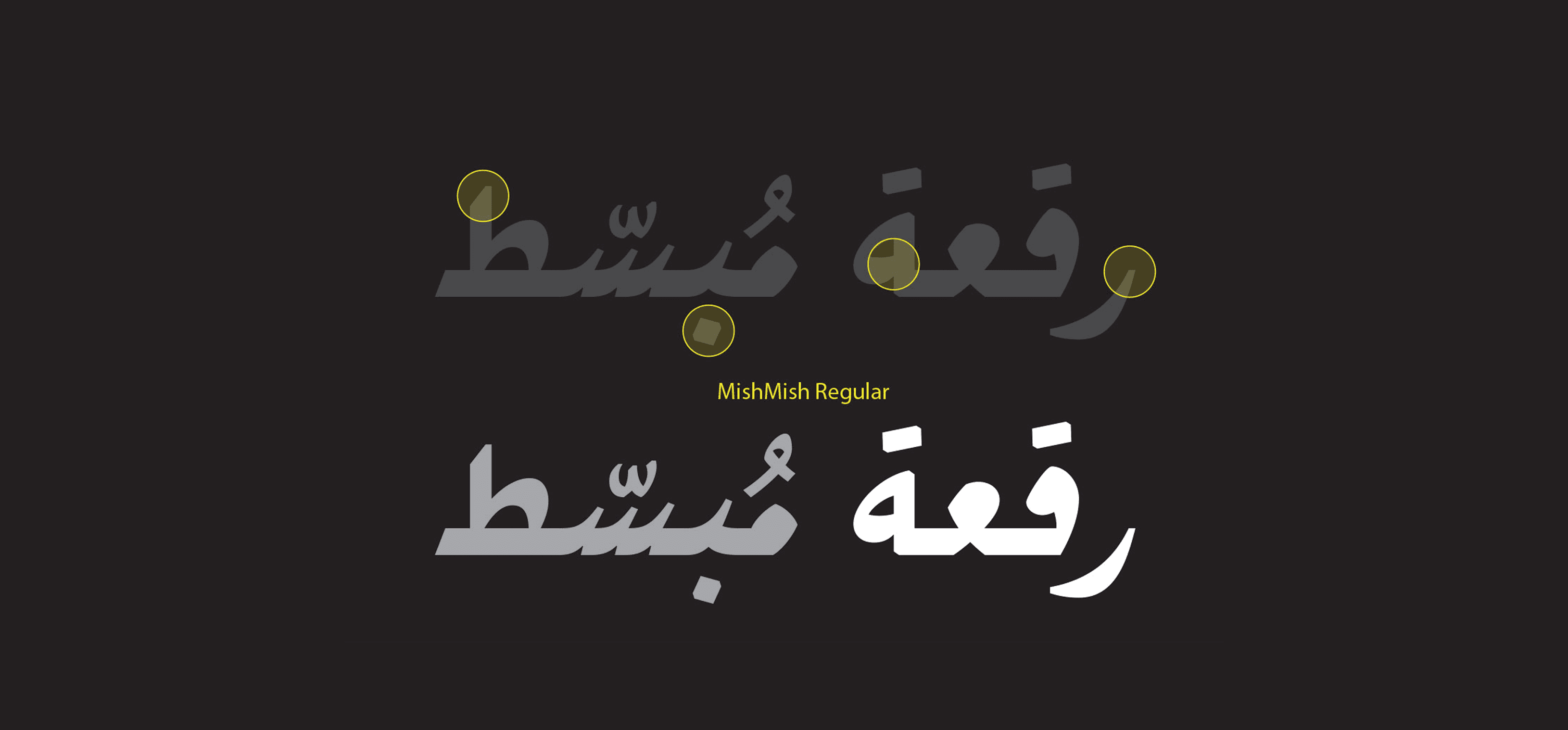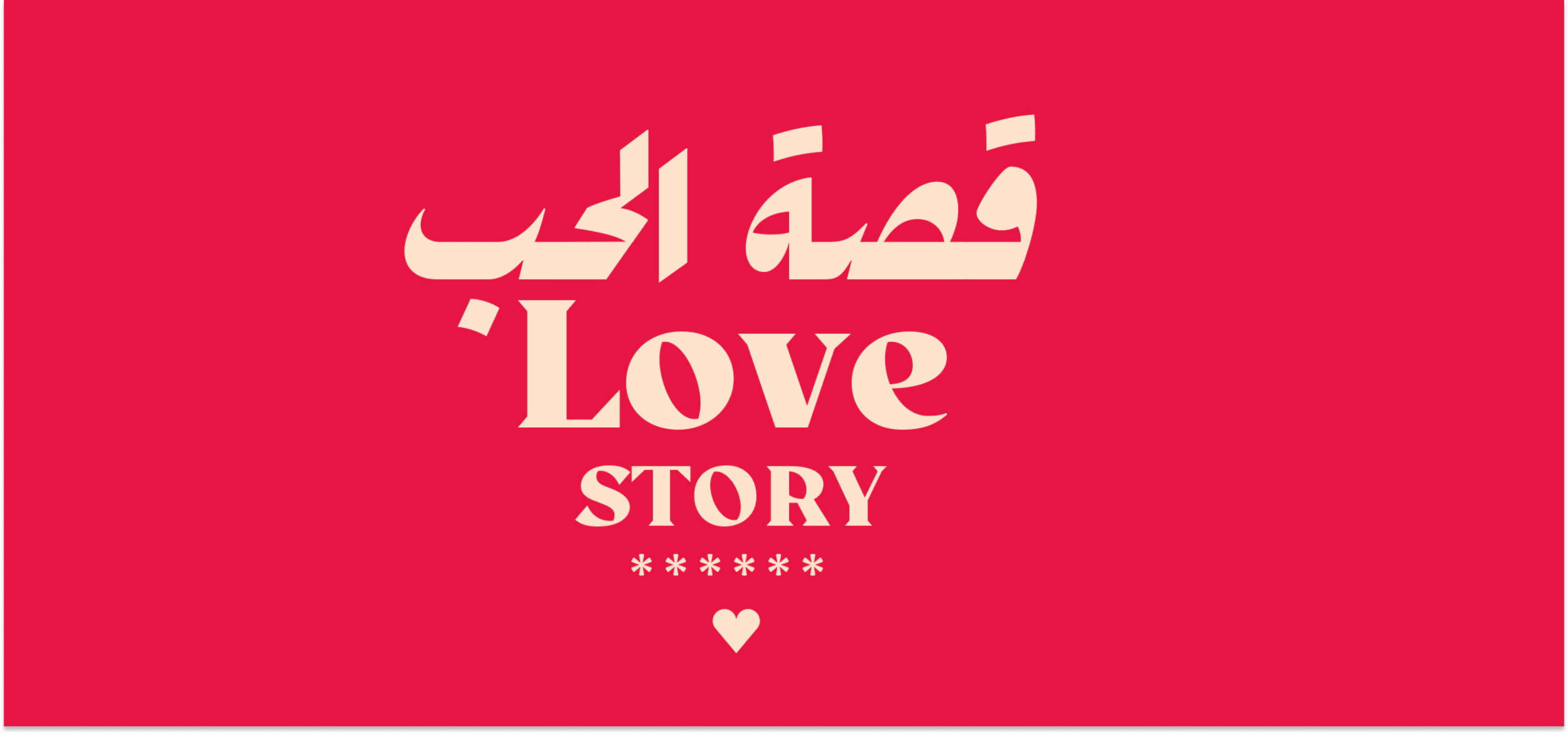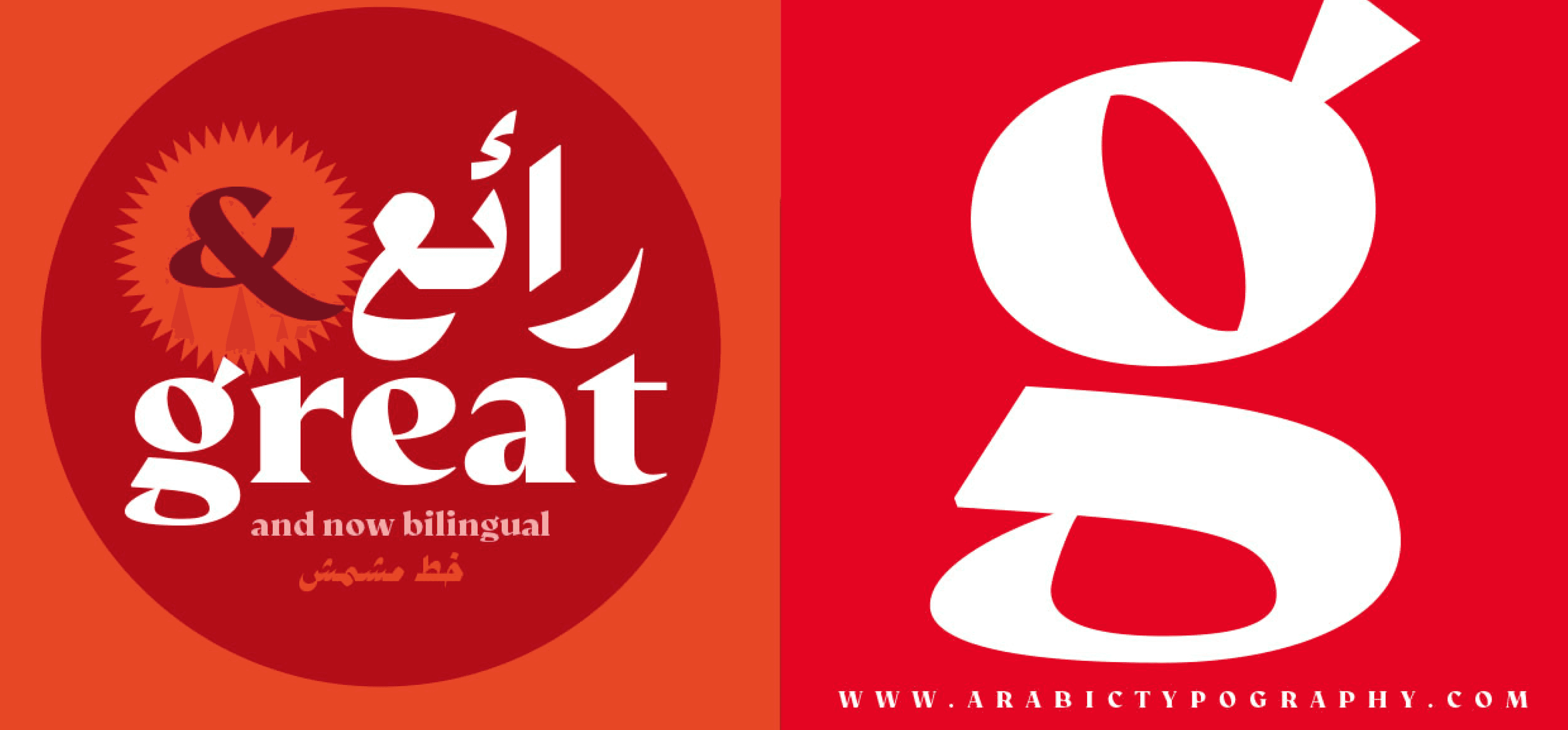
خط MishMish هو خط ثنائي اللغة (عربي + لاتيني) وُلد نتيجة سلسلة من التجارب الإبداعية المستوحاة من أسلوب الرقعة التقليدي في الخط العربي.
يعتمد تصميمه على هذا الأسلوب الشائع، لكنه يأتي بصيغة مبسطة دون التراكيب المعقدة، مع مجموعة واسعة من الربطات (Ligatures) التي تضيف طابعًا مميزًا ومتناغمًا للخط.
يتميز MishMish بتوازنه بين التراث والبساطة، مما يجعله مناسبًا للاستخدام في المشاريع المعاصرة متعددة اللغات.